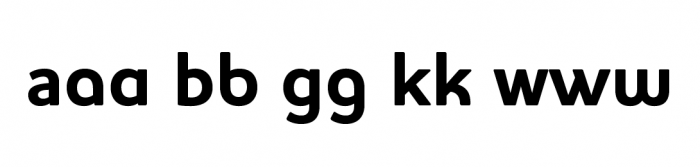
Opentype-Monster gesucht
ich suche eine Sansserif-Schrift, die „unglaublich“ viele Opentype-Features hat.
Zahlen sind für mich uninteressant, ich hätte gerne so viele verschiedene Buchstabenformen wie möglich.
Hier im Beispiel: Houschka.